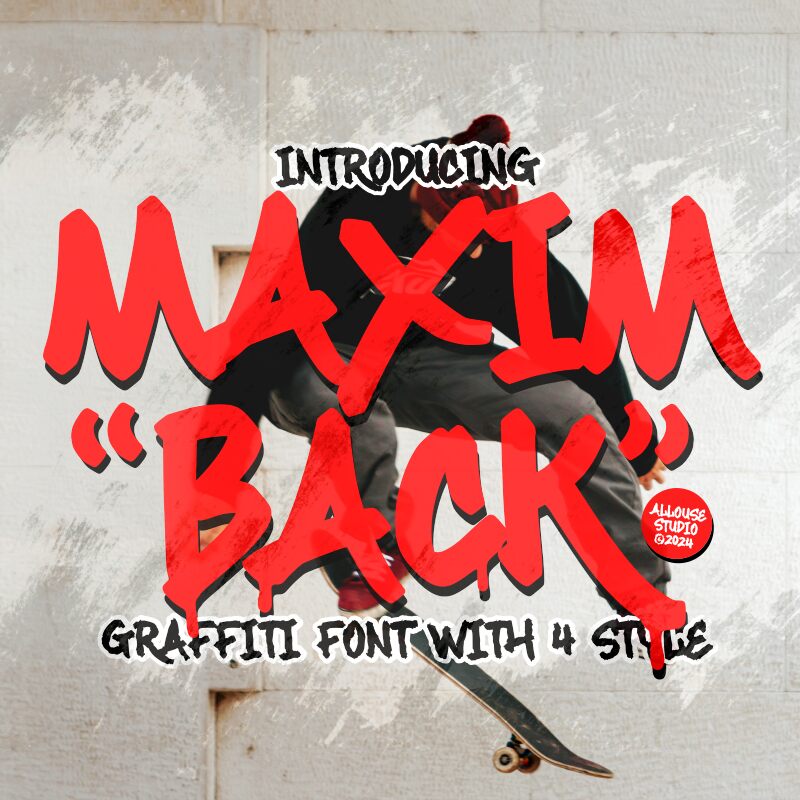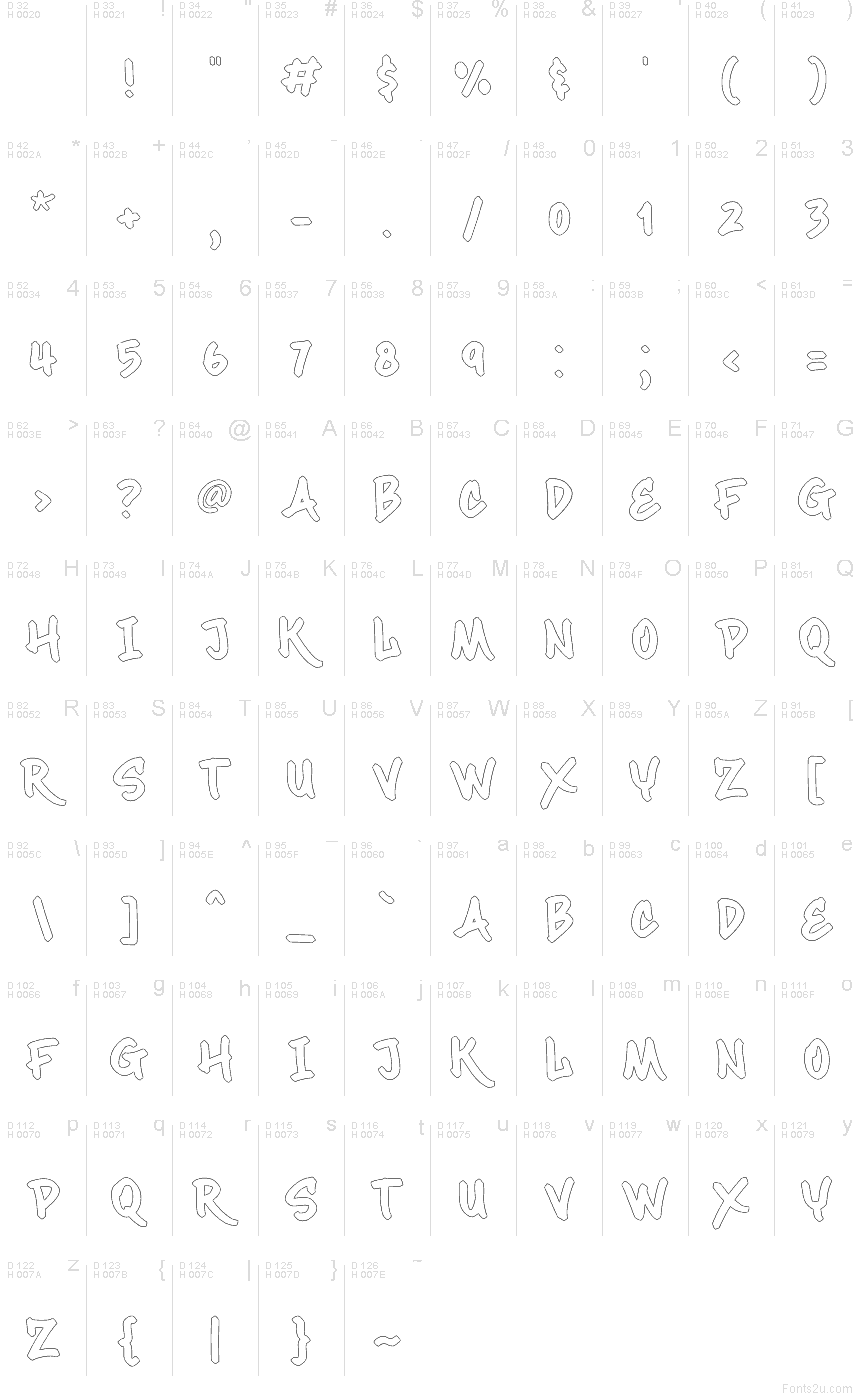
تعتبر خط Maximback Outline من Allouse.Studio خطاً مجانياً بنمط الجرافيتي، يتميز بصور ظلية منتفخة تشبه خط الماركر، مع خطوط خارجية حرة تحافظ على الطابع الخام والمكتوب يدوياً. تضفي الحواف غير المتساوية، والوصلات الزاوية، والتداخلات الطفيفة حيوية تشبه حيوية كتابات الشوارع العفوية، بعيداً عن الخطوط الكرتونية الصلبة.
تعتبر هذه الخطوط الخيار الأمثل للملصقات، وأغلفة الأشرطة (mixtapes)، ورسومات ألواح التزلج، ونشرات الفعاليات، وعناوين وسائل التواصل الاجتماعي، خاصةً عندما تبحث عن طابع حضري غير رسمي. بفضل خطوطه الخارجية المفتوحة وإيقاعه الواسع والمنتفخ، يستطيع Maximback Outline إبراز العناوين القصيرة وتصاميم الملصقات (stickers) وبضائع الهوية البصرية دون أن تبدو متكلفة.